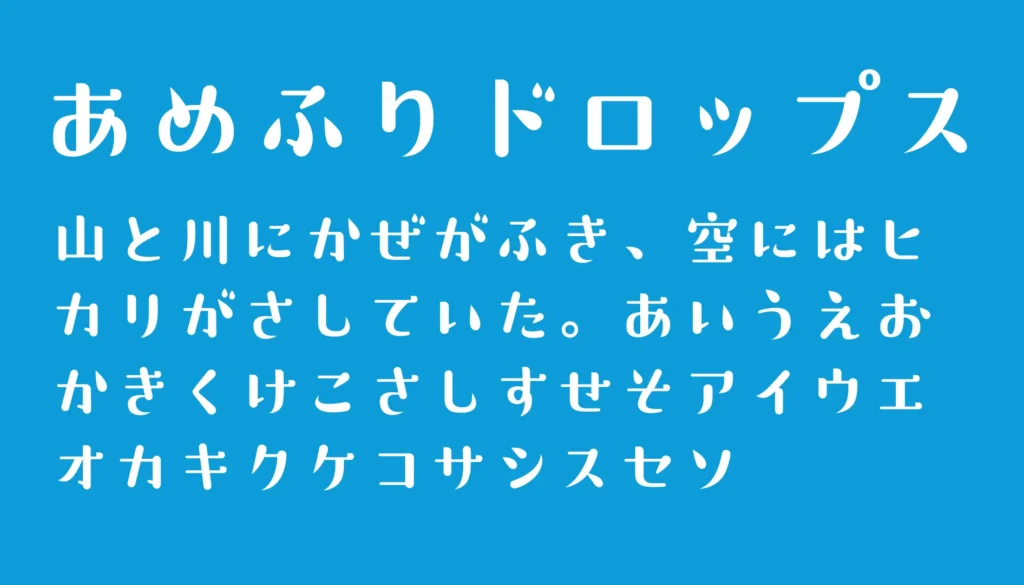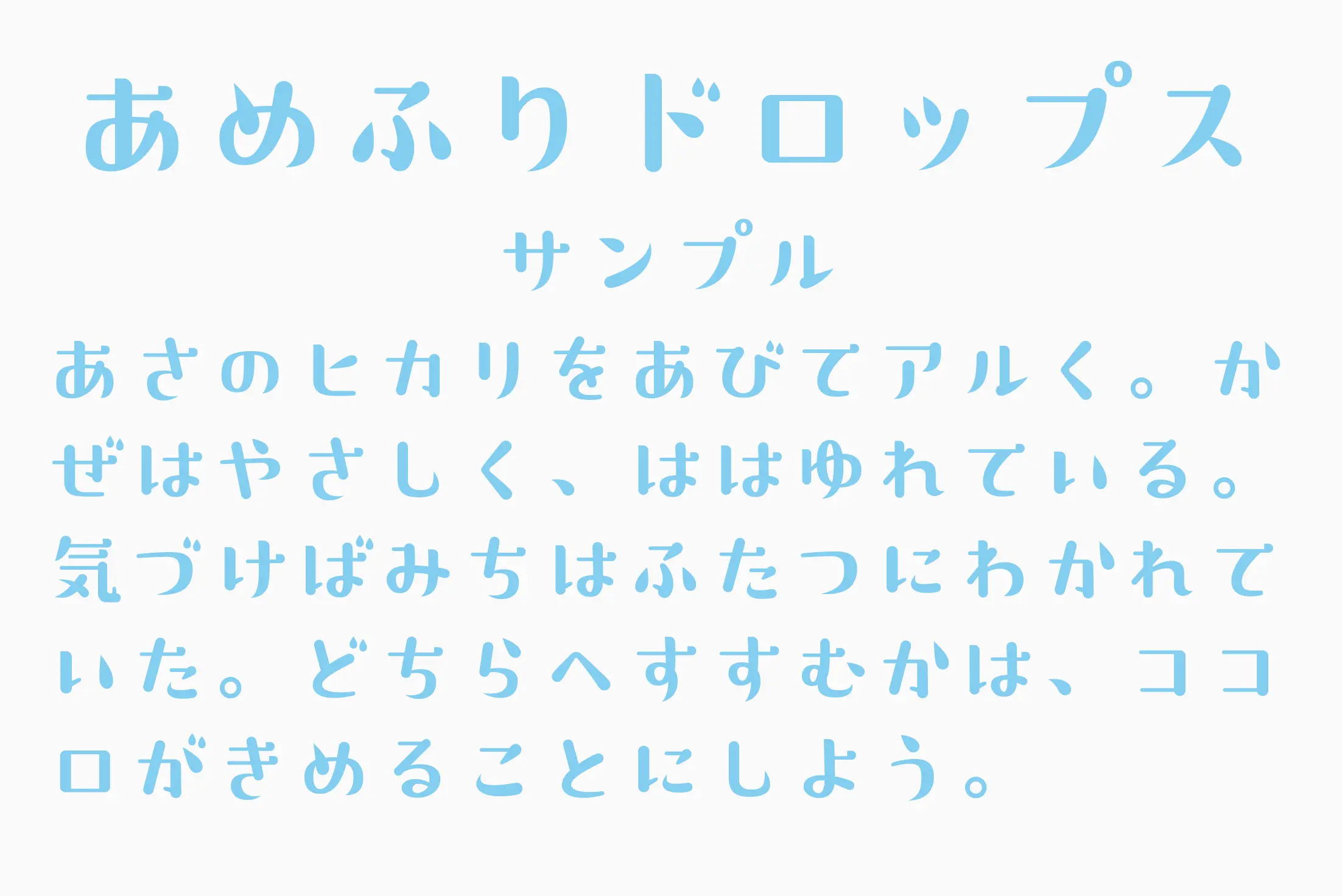
雫をモチーフにした、やさしくノスタルジックな雰囲気の日本語フォントです。丸みのある文字に、少しゆらいだようなリズムがあり、雨の日のきらめきや、懐かしい絵本のような空気感を演出できます。ひらがな・カタカナのやわらかい表情が特に魅力的で、かわいい見出し、季節バナー、サムネイル、ロゴ、ハンドメイド系のPOPなどにぴったり。
あめふりドロップス